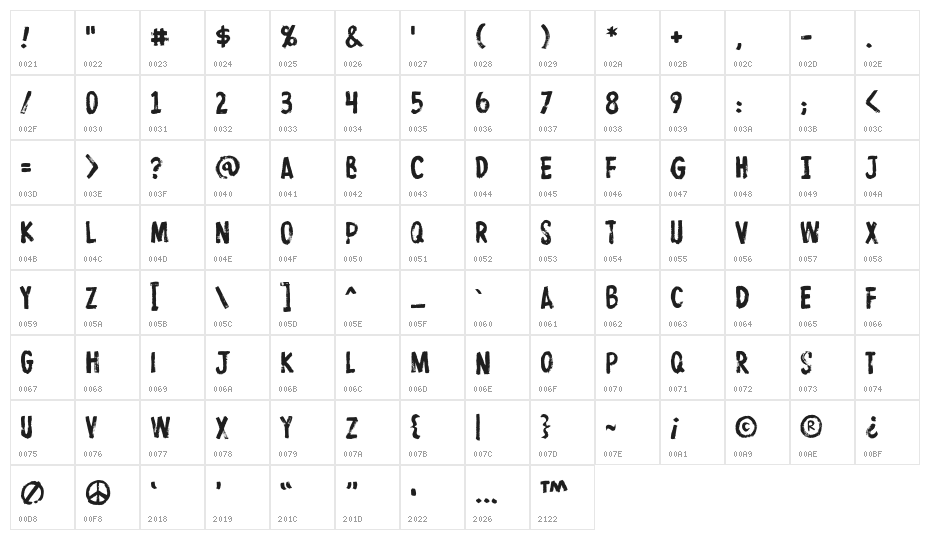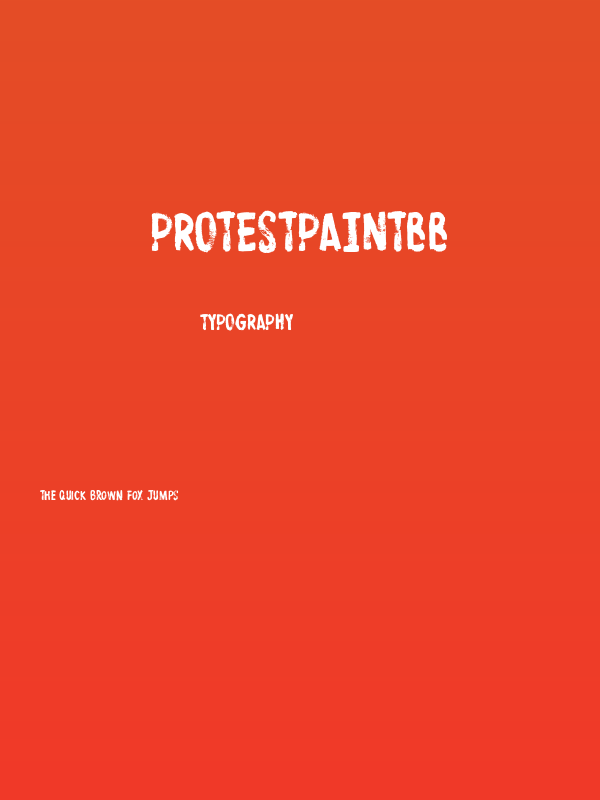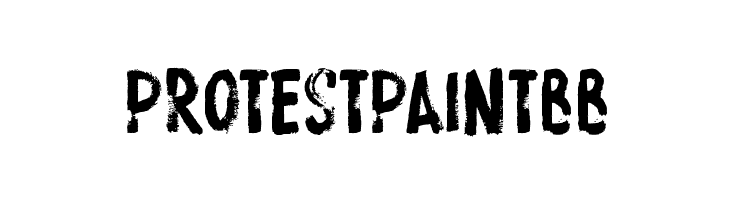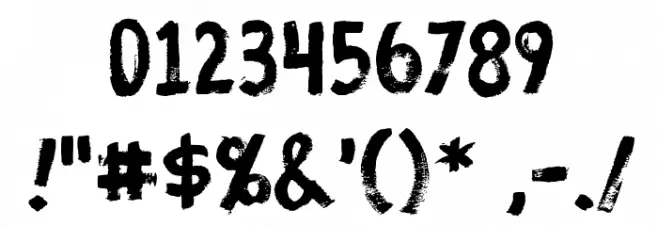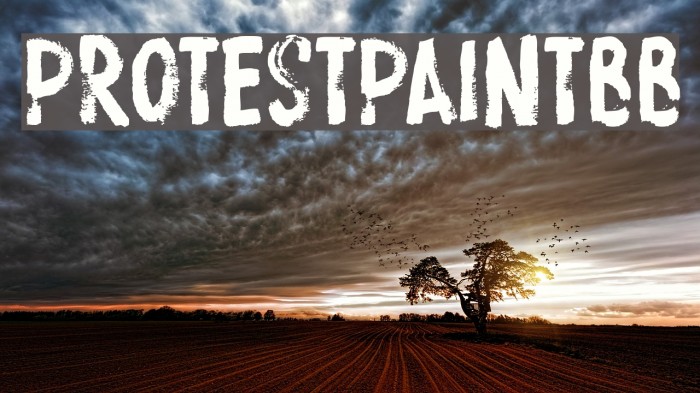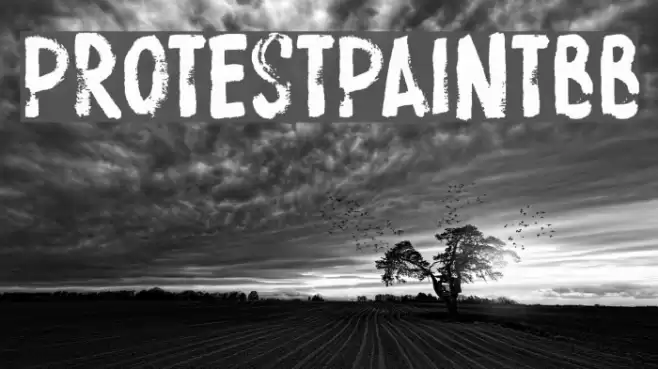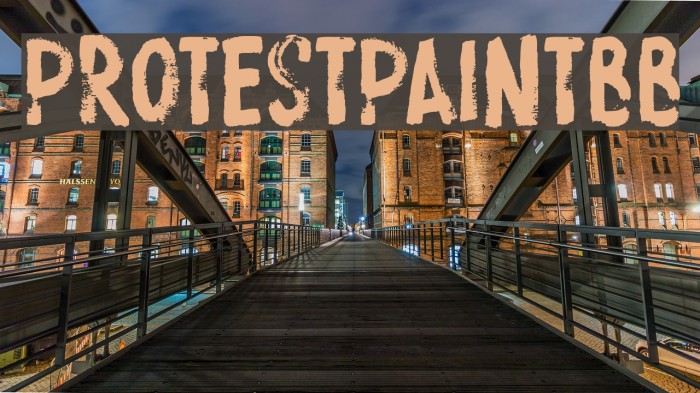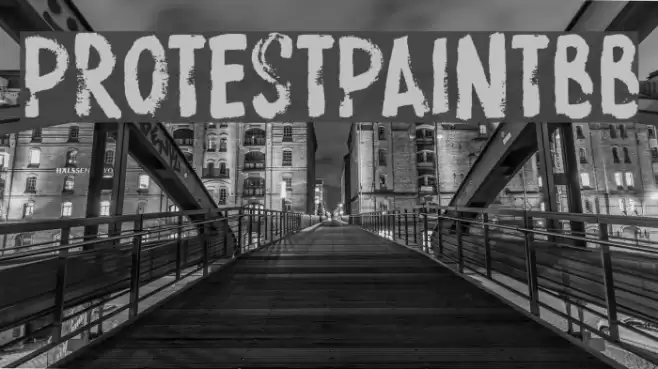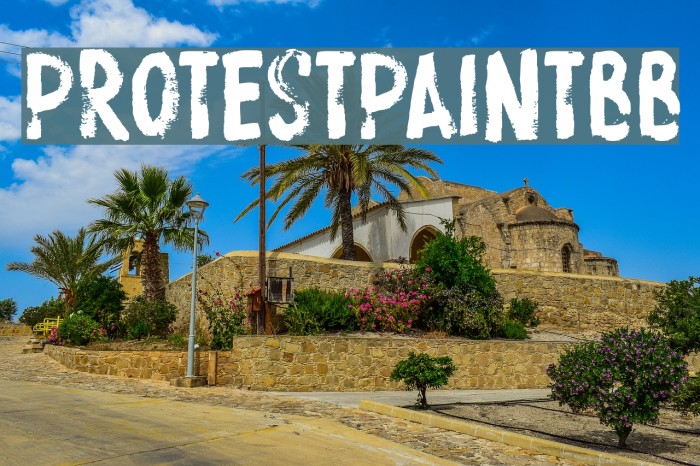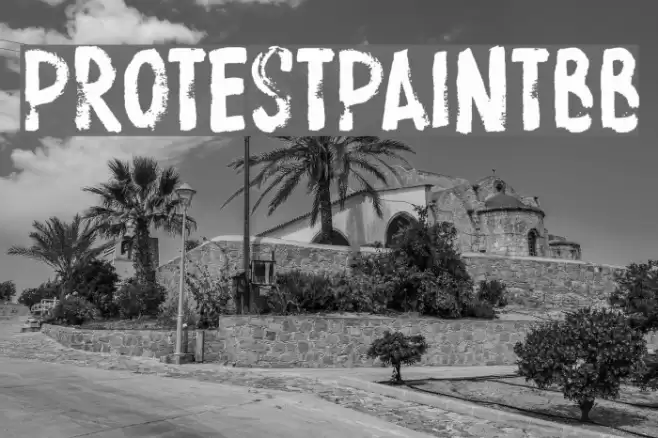
ProtestPaintBB Font
| Style général | Modern, Artistic |
| Cas d'utilisation | Headlines, Posters, Artistic Designs |
| Projets proposés | Ideal for protest posters, album covers, street art designs, and bold advertising campaigns. |